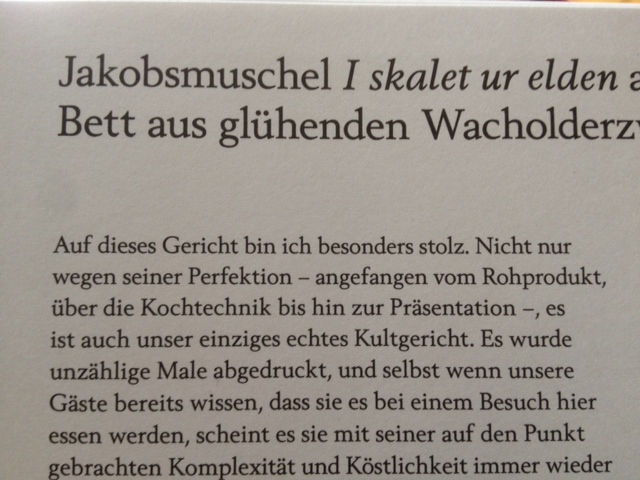
Texttype, Buch »Fäviken«
neuerdings ist mir im buch »fäviken« folgende texttype aufgefallen, aber leider nicht eingefallen.
zuerst dachte ich an die plantin, aber dazu ist sie in den details dann doch zu eigen … ich freu mich über ihren namen.